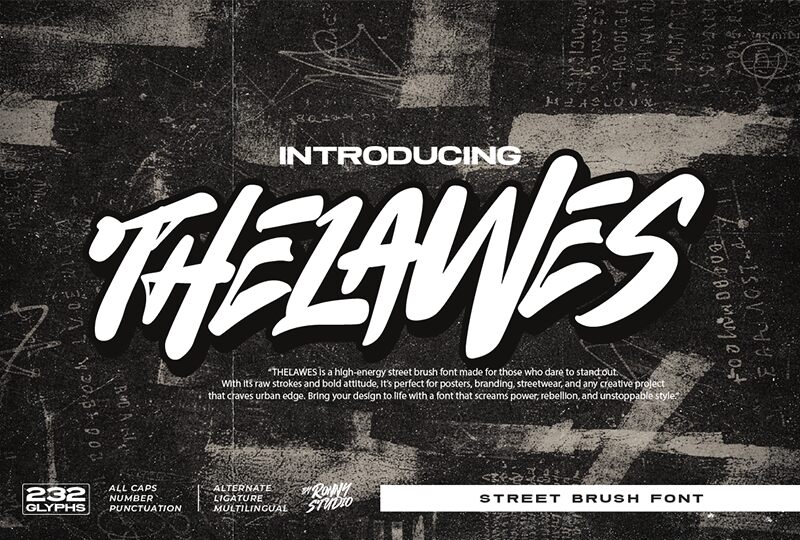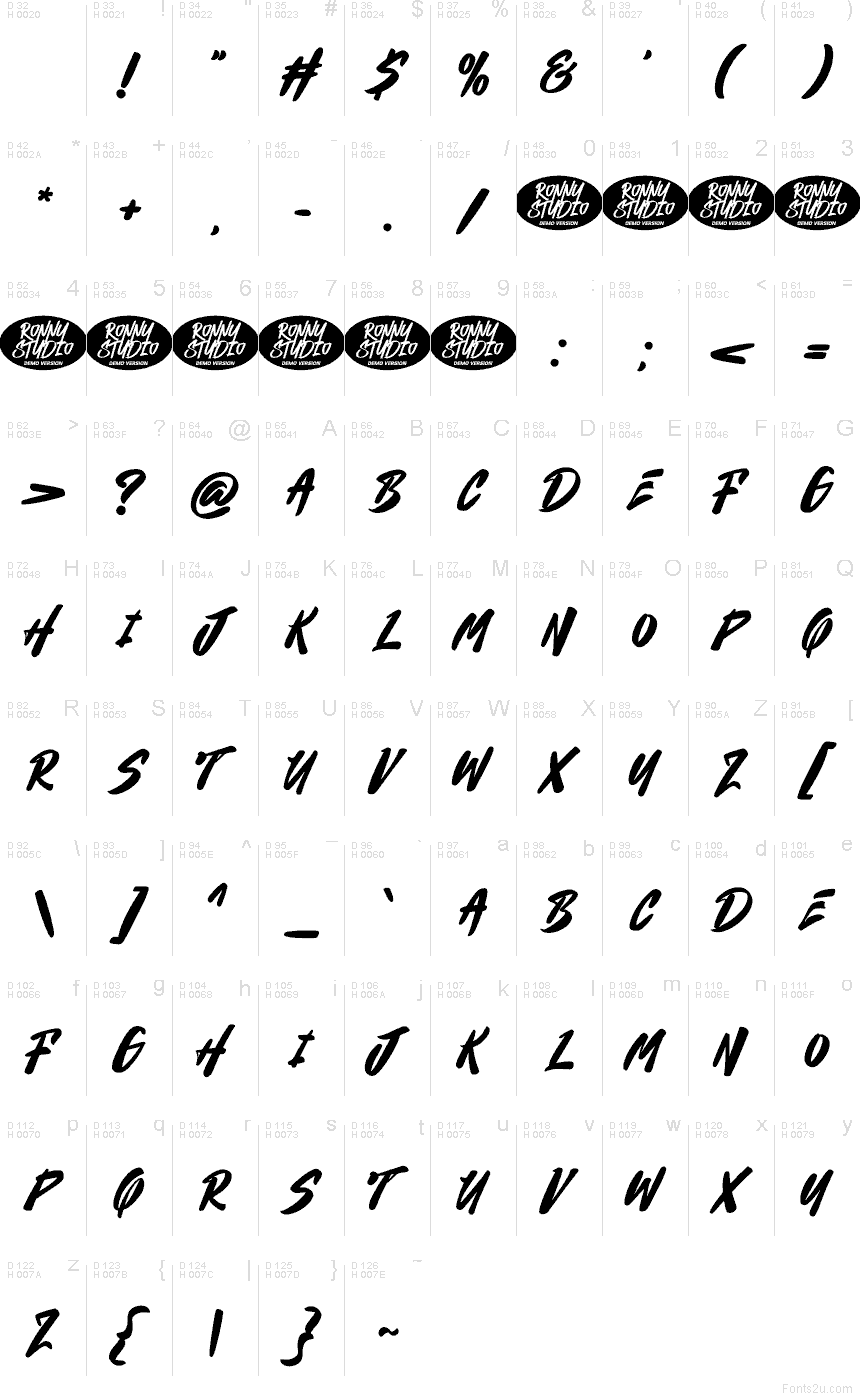
Font Thelawes od Rony Rizki Jaya z Ronny Studio přichází s dravou energií a rychlými tahy štětcem, které vypadají jako čerstvě nastříkaný tag – tlusté, inkoustové plochy, ostré detaily a šikmý rytmus, díky kterému písmo doslova žije. Je to bezplatné graffiti písmo a jeho syrovost působí téměř hmatatelně, jako barva, která se vpíjí do betonu, místo aby jen spočívala na nějaké mřížce.
S Thelawes dodáte tu správnou dávku postoje streetwearovým logům, obalům desek, skejťácké grafice, titulkům na plakátech, náhledům pro YouTube, letákům na akce nebo sadám samolepek, aniž byste ztratili na čitelnosti. Tento bezplatný font nejlépe vynikne, když mu dáte prostor – pracujte s velkými formáty, nechte rozestupy mírně otevřené a nechte tahy volně dýchat na čistém pozadí. Pro drobné texty, jako jsou kredity nebo data, jej zkombinujte s jednoduchým, robustním bezpatkovým písmem, aby váš tag zůstal hvězdou.